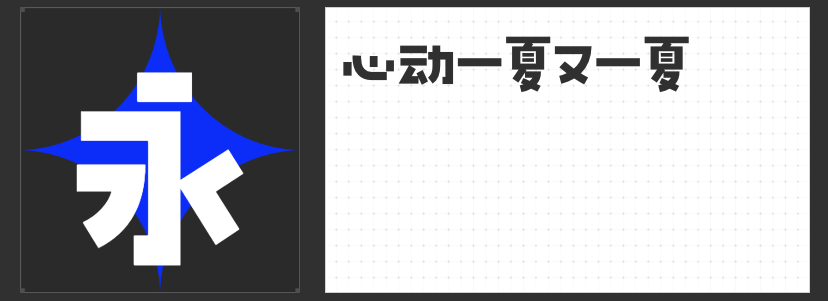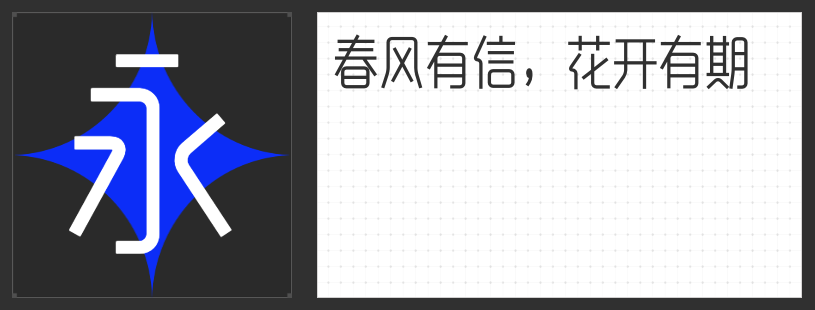
让字幕活起来!四款短视频爆款字体推荐
在15秒定生死的短视频江湖,字体不仅是信息载体,更是视觉节奏的掌控者。以下四款字体以独特个性化身镜头语言,助你的创意在方寸屏幕间破圈而出。
【字恋狂漫野 鸣风:手写呼吸感激活画面节奏】
这款字体如书法家即兴挥毫,直线骨骼勾勒出张弛有度的结构美学。错落字态与断开式笔画设计,让字幕自带呼吸韵律,尤其适合美食探店类视频——当镜头扫过滋滋作响的烤肉时,跳动的字体仿佛能闻到焦香。去钩处理与灰度均衡的特质,在美妆教程的快剪片段中,既能保持信息清晰,又增添时尚杂志般的排版质感。
【字恋狂澄空 鸣风:万能排版魔术师】
上松下紧的灵动结构堪称短视频排版救星!知识类口播视频用其展示要点时,字面随内容伸缩的特性让信息层级一目了然;旅行Vlog中搭配航拍大场景,低重心设计恰似地平线般稳定画面。平直切角的折笔处理,在科技产品开箱视频里既能表现数码产品的锐利线条,又不失人文温度。
【高手庆科静雅体 古朴版:文化类视频的时空隧道】
当非遗纪录片需要字幕承载岁月沉淀,这款圆体以青铜鼎纹般的圆润笔触,将现代汉字注入古典气韵。等粗笔形与圆角处理,在书法教学视频中既能清晰展示运笔轨迹,又避免生涩感。留白处的去钩设计,恰似古籍残卷般的留白意境,让文化类内容平添三分书卷气。
【字恋狂嗨玩简:短视频的视觉跳跳糖】
这款"笨拙萌"字体简直是搞笑短剧的定制皮肤!粗壮笔画如乐高积木般憨态可掬,在宠物日常视频里为喵星人对话增添萌感,在游戏解说中强化"菜鸟逆袭"的戏剧张力。靠下的重心设计,在竖版短视频中天然适配手机屏显,让"沙雕"弹幕自带喜感BGM。
从国风古韵到现代潮玩,这四款字体如同镜头里的百变演员:手写体能演绎市井烟火,圆体能诉说文化密码,萌系字体自带社交货币属性。在短视频的流量战争中,选对字体就像为内容装上视觉涡轮增压器——同样的文案,因字体不同,可能成就爆款,也可能湮没无声。